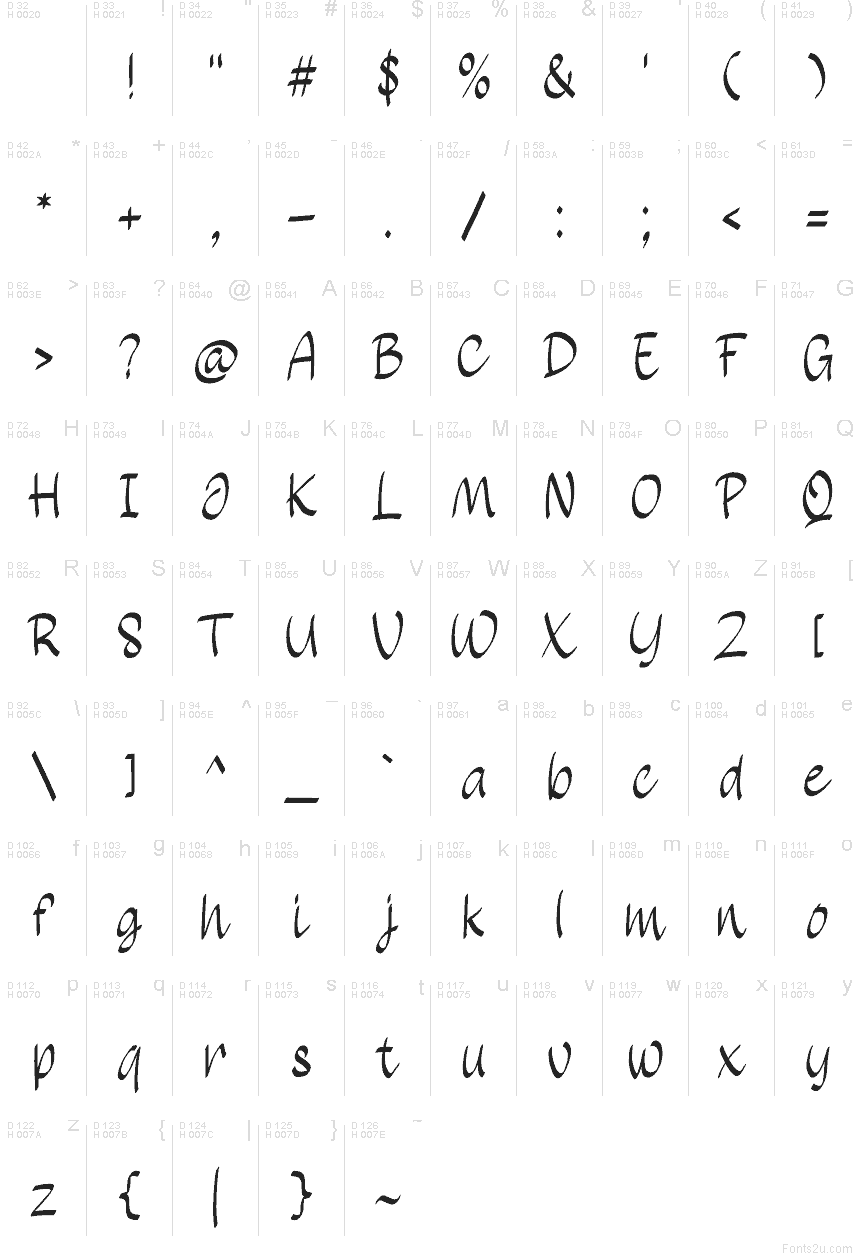
Toonizo هو خط مكتوب باليد مجاني يتميز بضربات عالية ومدببة ومنحنيات غير منتظمة قليلاً تمنحه طابعاً عفوياً وكأنه مرسوم بالحبر. تحافظ الحروف على إيقاع ضيق ومستقيم، مع أشكال دائرية ونهايات حادة تجعل الخط حيوياً دون أن يبدو فوضوياً.
يعمل Toonizo بشكل رائع مع عناوين القصص المصورة (الكوميكس)، والملصقات، وتصميم العلامات التجارية للأطفال، وملصقات المنتجات، وتصاميم الاقتباسات حيث تبدو اللمسة المرسومة باليد أكثر شخصية من الخطوط القياسية. يضفي هذا الخط المجاني حيوية على الشعارات والسطور القصيرة، خاصة عندما ترغب في أن يبدو الخط وكأنه رسم تخطيطي مباشر ومليء بالحركة.